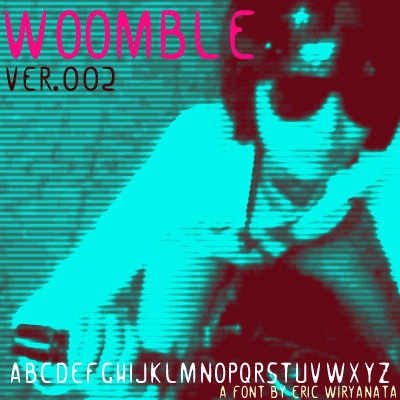
Woomble 002 di Eric Wiryanata è un carattere display gratuito in stile fumetto, con maiuscole alte e vivaci e un tocco disegnato a mano. Le lettere appaiono morbide e gomose, con forme tonde strette e un ritmo verticale irregolare che conferisce all'intero font un'impronta giocosa e leggermente traballante.
È ideale per copertine di libri per bambini, packaging di snack, titoli di poster, inviti per feste e semplici loghi che richiedono un font gratuito dal tono amichevole e fatto in casa. Le forme arrotondate e allungate e le maiuscole elastiche funzionano bene anche per titoli, brevi testi di banner e monogrammi, poiché le lettere mantengono il loro fascino anche quando usate parola per parola.
Di Eric Wiryanata. Dicembre 2006.
Woomble è stato preso da un frontman di una band.
Il design non è farina del suo sacco.
La seconda versione è una modifica dell'originale.